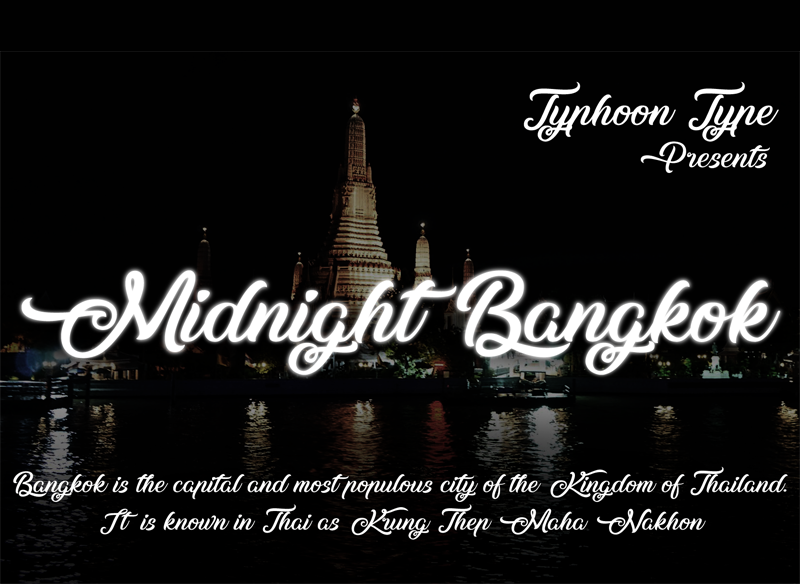
Introduzimos Midnight Bangkok Font para aqueles que buscam uma fonte script moderna e elegante. Desenvolvida pelo designer Typhoon Type – Suthi Srisopha, esta fonte é perfeita para criar logotipos memoráveis, rótulos de produtos inovadores e designs gráficos impressos e digitais, desde outdoors até a revendedora digital mais criativa. Com seu traçado sofisticado, Midnight Bangkok captura o espírito vibrante da capital tailandesa, trazendo uma sensação de modernidade e sofisticação para seus projetos visuais. Não importa se você está planejando criar rótulos ou um cartão de visita, Midnight Bangkok tem a solução perfeita para fazer seu trabalho ainda mais brilhante.